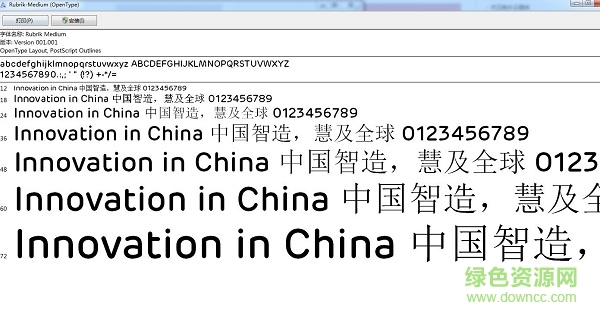
rubrik字體是一款筆形柔和的英文廣告字體,不粗不細(xì),線條偏于圓形,結(jié)構(gòu)對(duì)稱,構(gòu)思精巧,多用于美術(shù)設(shè)計(jì)或是產(chǎn)品包裝設(shè)計(jì),喜歡的朋友快來下載吧!
【等線字體】:字形的特點(diǎn)幾乎都是由相等的線條構(gòu)成;
【裝飾字體】:對(duì)各種字體進(jìn)行裝飾設(shè)計(jì),變化加工,達(dá)到引人注目,富于感染力的藝術(shù)效果!